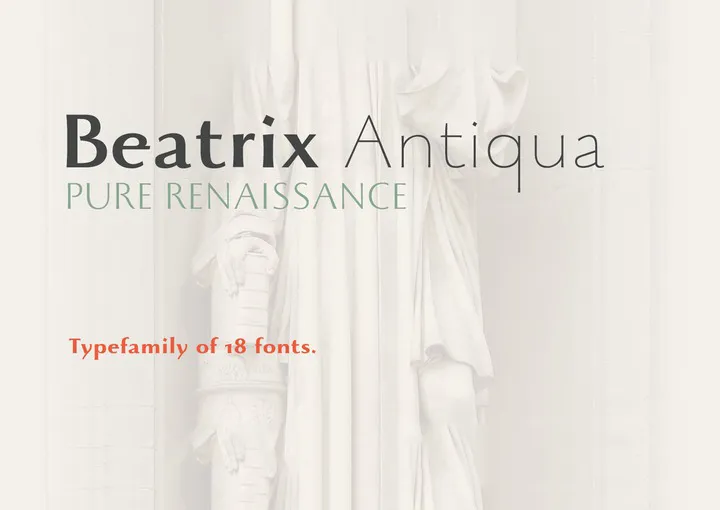
Através de uma colaboração entre Francesco Canaoraro, Beatrix Antiqua é apresentada como uma nova família de fontes serifadas. Seu design é inspirado nas capitalizas romanas clássicas que evocam as carvagens em granito na Catedral de Santa Croce em Florença, onde os arcos são frequentemente removidos enquanto mantém-se a largura variável dos traços. Nesta família de fontes Beatrix, é possível notar uma elegância refinada que se destaca através da presença do famoso modelo monumental. As capitalizas deste tipo de fonte têm sua origem direta nas estruturas arquitetônicas em Florença, tornando-as únicas e distintivas. A antiga influência romana é evidente na Beatrix Antiqua, que oferece uma combinação harmoniosa entre o clássico e o moderno. Nesta família de fontes, a Beatrix Antiqua não apenas oferece um estilo único, mas também uma versatilidade para uso em uma variedade de aplicações. Suas linhas sutilmente definidas se assemelham àqueles que transmitem confiança e sofisticação, tornando-a uma escolha perfeita para designers que valorizam tanto o estilo clássico quanto a elegância moderna. Beatrix Antiqua não é apenas uma fonte; ela é um complemento versátil que transforma qualquer projeto em algo de que você pode orgulhar-se. Com sua capacidade de criar títulos impactantes ou textos mais sutis, este design oferece uma gama de opções para atingir seus objetivos gráficos.